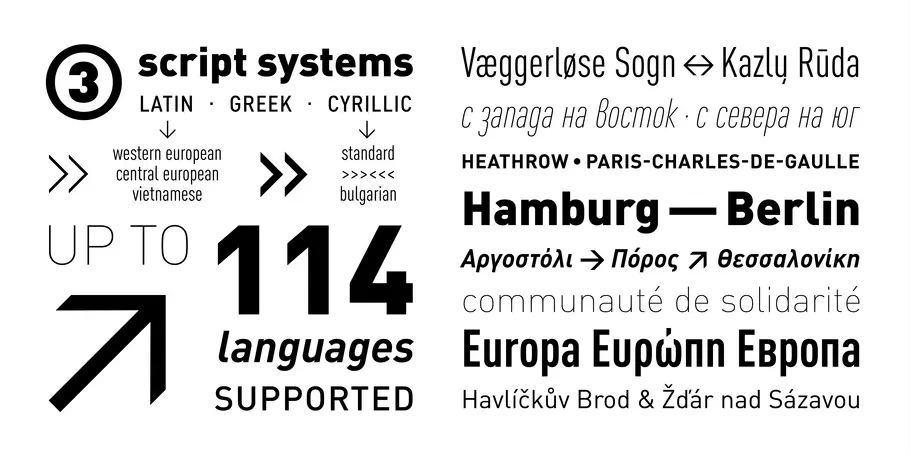
FF DIN Variable
Mais FF DIN do que nunca.
A precisão é o mantra da FF DIN, e essa filosofia de design também se faz presente na FF DIN Variable. FF DIN Variable: mais FF DIN do que nunca. Levando a tecnologia de fonte a seu limite, as fontes Variáveis oferecem aos criativos uma ferramenta para acessar variações específicas que se destacam em qualquer espaço de design.
FF DIN: a famosa primeira releitura da DIN 1451. A FF DIN foi inspirada nos modelos de letras da norma padrão alemã DIN 1451 e é considerada a fonte padrão perfeita devido ao seu design metódico e planejado.
FF DIN Variable: mais FF DIN do que nunca. Levando a tecnologia de fonte a seu limite, as fontes Variáveis oferecem aos criativos uma ferramenta para acessar variações específicas que se destacam em qualquer espaço de design. A FF DIN Variable usa uma. engenharia ousada para mesclar a aparência técnica da FF DIN com o mundo suave e orgânico das fontes variáveis.
Disponível nos estilos verticais e itálicos, há muito mais a ser descoberto sobre a FF DIN com a nova era da tecnologia de fontes. A FF DIN Italic tem um estilo romano inclinado, no entanto, ela é corrigida opticamente, um pouco mais fina e estreita. Como resultado, a FF DIN Italic se destaca com sutileza.
A FF DIN Variable permanece fiel a seu DNA, tomando muito cuidado para garantir que as novas instâncias da FF DIN Variable permaneçam consistentes com todos os pesos conhecidos. A precisão é o mantra da FF DIN, e essa filosofia de design também se faz presente na FF DIN Variable. Ela produz uma tipografia ajustada minuciosamente e títulos animados expressivos para qualquer design.
Estilos infinitos, inteligentes e eficazes.
Albert-Jan Pool nasceu em Amsterdã em 9 de julho de 1960. Após estudar na Royal Academy of Arts (KABK) em The Hague com Gerrit Noordzij, ele foi para Hamburgo em 1987 e trabalhou na Scangraphic e na URW. Desde 1994, ele tem seu próprio estúdio, o Dutch Design, e cria fontes, como FF OCR-F e FF DIN e fontes corporativas para Jet/Conoco, C&A e HEM/Tamoil.
Antonia Cornelius é designer de comunicação e fontes, professora, autora e pesquisadora alemã que se interessa especialmente pela legibilidade e inteligibilidade. Ela estudou design de comunicação com ênfase em design de fontes com Jovica Veljović na Universidade de Ciências Aplicadas em Hamburgo. Logo após concluir seu mestrado, Antonia se juntou ao Dutch Design para expandir a família FF DIN com a FF DIN Slab. Após isso, ela projetou cuidadosamente os contornos da FF DIN e da FF DIN Stencil para transformá-las em fontes variá.
Achaz Reuss se formou como designer de comunicação na Universidade de Ciências Aplicadas em Hamburgo em 1983. Depois, ele trabalhou na URW, como designer de fonte e fundou sua agência, a Reuss Design, em 1995 especializada em fontes e design corporativos. Ele criou as fontes das marcas NIVEA e Milram. Sua família de fontes FF QType foi publicada pela FontShop em 2004. Em 1995, ele participou dos primeiros cinco pesos da fonte FF DIN de Albert-Jan Pool e criou a FF DIN Stencil, que foi lançada em 2022.